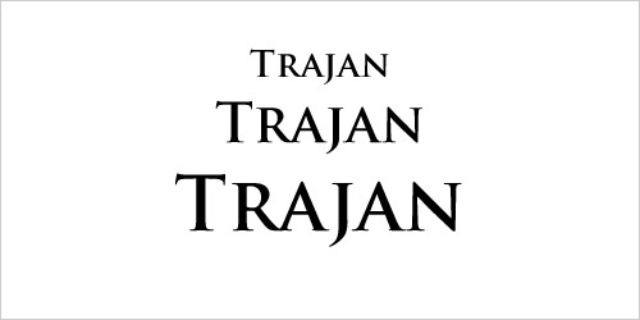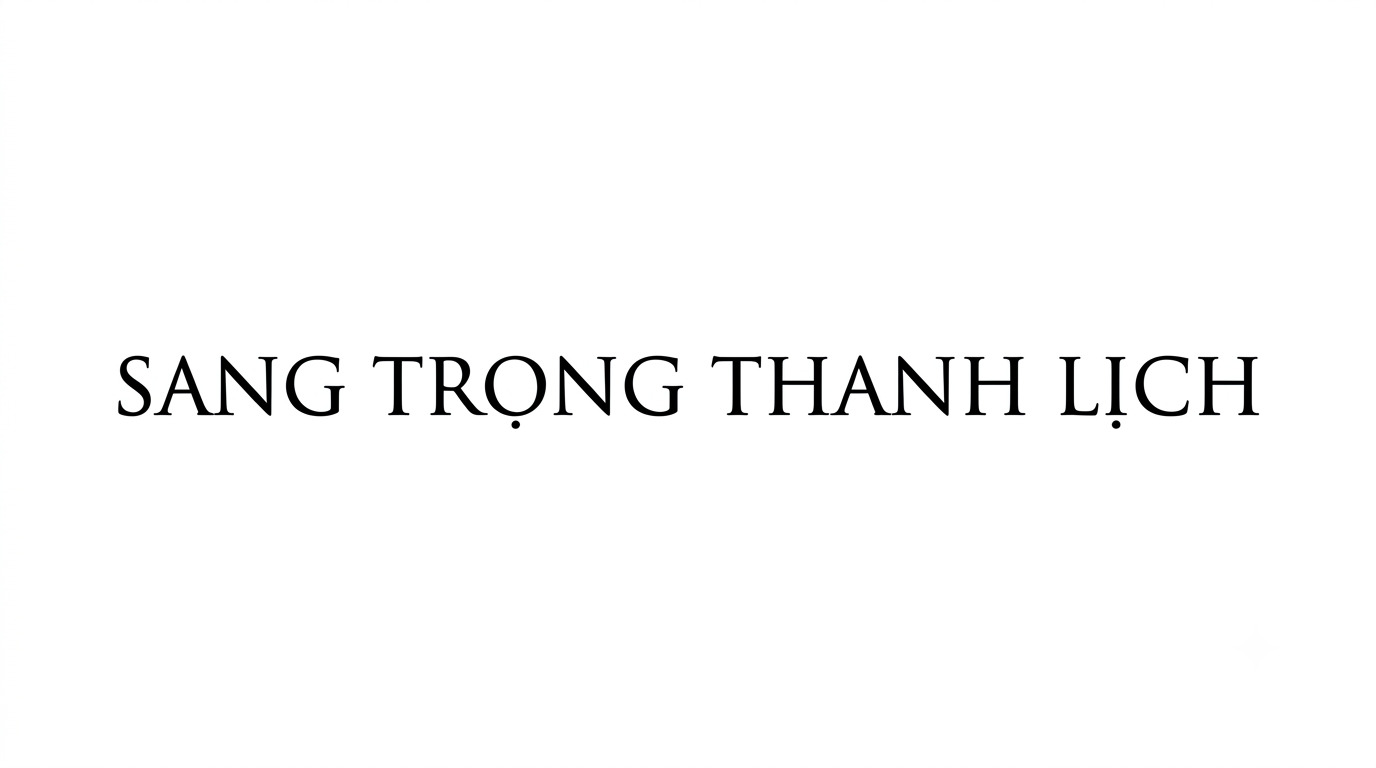
Nhiều designer khi sử dụng font Trajan Pro thường gặp tình trạng không hỗ trợ đầy đủ ký tự tiếng Việt, dấu thanh bị lệch vị trí hoặc đường nét chữ bị giảm độ sắc nét khi in trên hộp quà, bao bì cao cấp. Những lỗi kỹ thuật này có thể làm mất đi vẻ trang trọng đặc trưng của kiểu chữ La Mã cổ điển, khiến thiết kế thương hiệu thiếu sự đồng nhất và chuyên nghiệp.
Font Trajan Pro và giá trị thẩm mỹ trong đồ họa
Trajan là một phông chữ thuộc dòng Serif (chữ có chân) mang tính biểu tượng, được Carol Twombly thiết kế cho Adobe vào năm 1989. Lấy cảm hứng từ những bản khắc trên cột trụ Trajan tại Rome, phông chữ này đại diện cho sự uy quyền, vĩnh cửu và tinh tế của kiến trúc La Mã cổ đại. Một đặc điểm thú vị là Trajan nguyên bản không có chữ thường, mọi ký tự đều được trình bày ở dạng chữ in hoa với các đường nét thanh mảnh nhưng vô cùng vững chãi.
Phông chữ này đã trở thành lựa chọn ưu tiên cho các poster phim điện ảnh, bìa sách nghệ thuật và bộ nhận diện của các nhãn hàng xa xỉ. Với sự ra đời của Font Trajan Pro 3, bộ phông này đã được mở rộng thêm nhiều độ dày (weights) và tinh chỉnh kerning để đạt độ cân đối cao hơn. Tuy nhiên, để sử dụng hiệu quả tại thị trường Việt Nam, việc tìm kiếm bản việt hóa chuẩn là rất quan trọng nhằm đảm bảo các dấu thanh không làm phá vỡ cấu trúc nghiêm cẩn của bộ chữ gốc.
5 ứng dụng nổi bật của font Trajan Pro Việt hóa trong in ấn
Nhờ phong cách cổ điển, trang trọng với cảm hứng từ chữ khắc La Mã, font Trajan Pro Việt hóa phù hợp với các thiết kế yêu cầu hình ảnh chuyên nghiệp, cao cấp và chỉn chu:
- Thiết kế bao bì yến sào và mỹ phẩm cao cấp: Trajan Pro thường được sử dụng trên hộp giấy Ivory, hộp cứng quà tặng để thể hiện tên thương hiệu và dòng sản phẩm. Các đường nét Serif đặc trưng giúp bao bì mang cảm giác sang trọng, phù hợp với các dòng sản phẩm quà biếu.
- Sản xuất bộ quà tặng văn phòng in logo: Font Trajan Pro phù hợp để in tên doanh nghiệp, slogan trên bình giữ nhiệt kim loại, sổ tay da hoặc bút ký. Kiểu chữ mạnh mẽ giúp logo giữ được vẻ trang trọng khi ứng dụng trên các sản phẩm quà tặng.
- In thiệp mời và bằng khen vinh danh: Những thông điệp sử dụng Trajan Pro trên giấy mỹ thuật có vân phù hợp với các sự kiện như lễ kỷ niệm, hội nghị, chương trình vinh danh hoặc quà tặng tri ân đối tác.
- Khắc laser quà tặng gỗ và kim loại: Logo dùng font Trajan Pro khi khắc trên gỗ tre, inox hoặc kim loại tạo điểm nhấn rõ ràng nhờ cấu trúc chữ cân đối, phù hợp với các sản phẩm quà tặng doanh nghiệp.
- In logo lên bộ ấm chén sứ quà tặng: Font Trajan Pro có thể kết hợp cùng kỹ thuật in nung trên men sứ để tạo họa tiết thương hiệu mang phong cách cổ điển, phù hợp với các sản phẩm quà tặng đối tác.
5 lưu ý khi sử dụng font chữ Trajan Pro trong in ấn
Để font Trajan Pro hiển thị rõ nét trên thành phẩm thực tế, designer nên chú ý các yếu tố kỹ thuật sau:
- Lưu ý đặc điểm chữ in hoa: Trajan Pro được thiết kế chủ yếu với hệ thống chữ in hoa. Khi sử dụng cho nội dung dài, nên kết hợp cùng font chữ dễ đọc hơn để bố cục không bị nặng nề.
- Kiểm soát độ dày nét chữ: Trajan Pro có sự tương phản giữa nét thanh và nét đậm. Khi in logo hoặc chữ kích thước nhỏ trên tem nhãn, nên lựa chọn kích thước phù hợp để các chi tiết mảnh vẫn được thể hiện rõ.
- Tối ưu đường Path khi gia công bế nổi: Khi sử dụng Trajan Pro cho logo dập nổi trên hộp quà, cần xử lý các điểm neo ở phần chân chữ Serif trong file vector. Việc này giúp khuôn bế thể hiện đúng hình dáng chữ và hạn chế lỗi trong quá trình gia công.
- Điều chỉnh khoảng cách ký tự (Kerning): Các tiêu đề dùng Trajan Pro thường có khoảng cách chữ rộng. Designer nên tinh chỉnh Tracking và Kerning để tên thương hiệu cân đối hơn khi đặt trên nắp hộp hoặc bề mặt sản phẩm.
- Kiểm tra màu sắc khi ép kim: Trajan Pro phù hợp với các kỹ thuật như ép kim vàng, bạc hoặc đồng. Cần kiểm tra thông số màu và mẫu thử trước khi sản xuất để đảm bảo hiệu ứng gia công phù hợp với thiết kế.